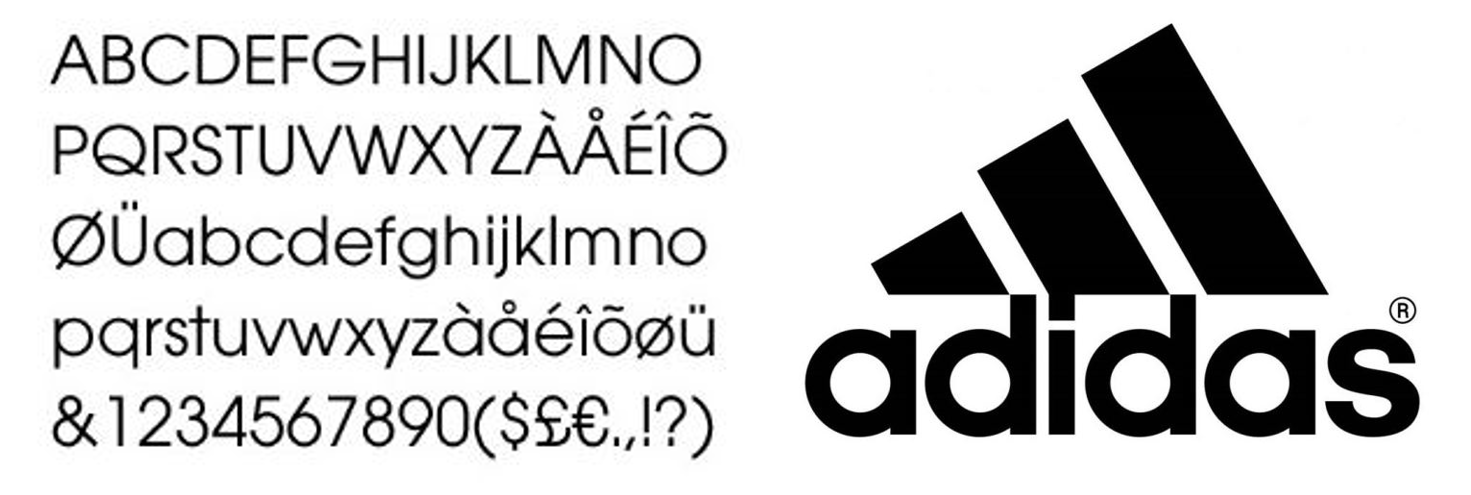
아방가르드(Avant Garde) 타이포그래피 디자이너, 허브 루발린(Herb Lubalin)
“아방가르드하다.”
보통 기존의 틀을 깨고 무언가 새로운 시도를 할 때 그런 표현을 쓰곤 한다. 대표적인 사례로 누에고치 같은 옷을 입은 모델들이 등장하는 꼼데가르송 패션쇼를 들 수 있다. 독특한 옷을 보고 난해하다는 생각이 앞서는 것은 아마 낯설기 때문일 것이다. 상징주의적 타이포그래피의 한 획을 그은 디자이너, 허브 루발린(Herb Lubalin, 1918~1981)의 행보도 그 시대 사람들에게 아방가르드함을 선사했다.
허브 루발린은 1960~70년대 미국의 대표적인 타이포그래피 디자이너이자 아트디렉터이다. 기존 타이포그래피가 의미나 정보를 전달하는 데 중점을 두었다면, 그는 이러한 경향을 해체하고 글자를 이미지화 하려 했다. 1964년에 허브 루발린사를 설립하면서 상상력 넘치는 스타일을 계속 시도했고, ‘루발린식 상징주의 타이포그래피’를 선보였다. 그가 디자인한 잡지 제호 『마더 앤드 차일드Mother and Child』를 보면, 타이포그래피가 시각 이미지 역할도 수행할 수 있음을 보여준다. 알파벳 ‘O’안에 ‘&’과 CHILD가 작게 들어가면서 마치 태아의 모습을 연상시키기 때문이다.
허브 루발린은 혁신적인 잡지 디자인을 도맡아 하며 자신만의 편집디자인을 개척해갔다. 1968년에 창간된 『아방가르드Avantgarde』는 그의 대표작이면서 세계적으로 유명한 ‘아방가르드 고딕(Avantgarde Gothic)’ 폰트가 탄생한 잡지이다. 전후 미국 사회의 흐름과 진보적이고 전위적인 예술을 담아낸 잡지의 제호답게 아방가르드 고딕체는 대중에게 기존에 볼 수 없던 새로움을 던져주었다. 특히 대문자 G와 A의 결합은 ‘대체 활자쌍’으로 불리며 타이포그래피 표현의 다양성을 넓혔다.
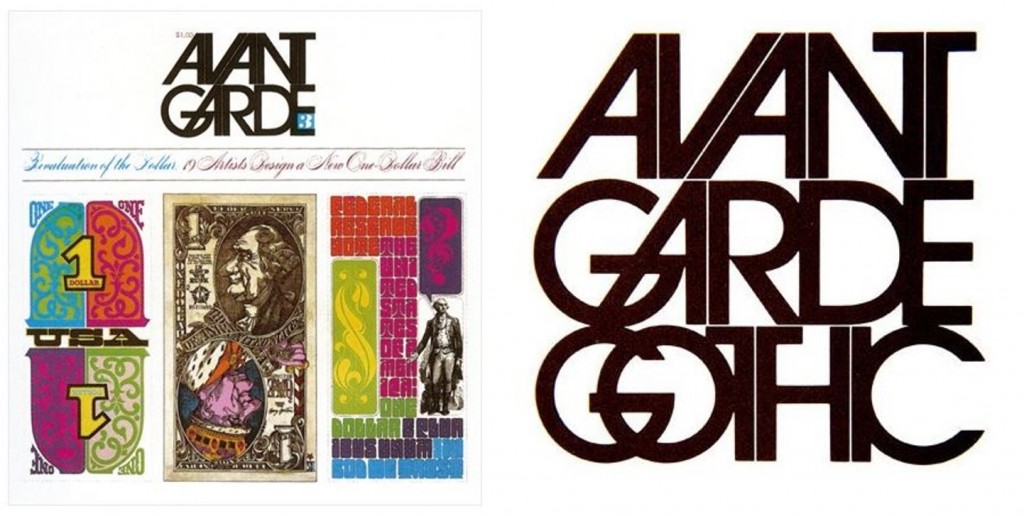
아방가르드 고딕체는 본래 대문자만 개발되었지만, 루발린이 동료들과 함께 만든 폰트 회사 ITC(International Typeface Corporation)를 통해 상업적으로 출시되면서 소문자와 기타 부호들도 함께 완성되었다. 20세기에 많은 사랑을 받은 아방가르드 고딕체는 아디다스 로고, 돌체앤가바나 로고 등 다양한 브랜드의 정체성을 드러내는데 사용되었다.
하지만, 허브 루발린의 의도와는 다르게 무분별하게 폰트가 사용되었고 이를 보며 후배 디자이너들은 안타까움을 표했다고 한다. 대체 문자쌍이 없고, 자간을 조절하지 않은 아방가르드 고딕체는 확실히 긴장감이 떨어진 모습으로 보여진다.
당연히 여기던 것에 의문을 갖고, 경계를 허무는 작업을 보여준 허브 루발린. 1984년, 뉴욕에는 허브 루발린 연구소가 세워져 그의 도전정신이 이어져 오고 있다.